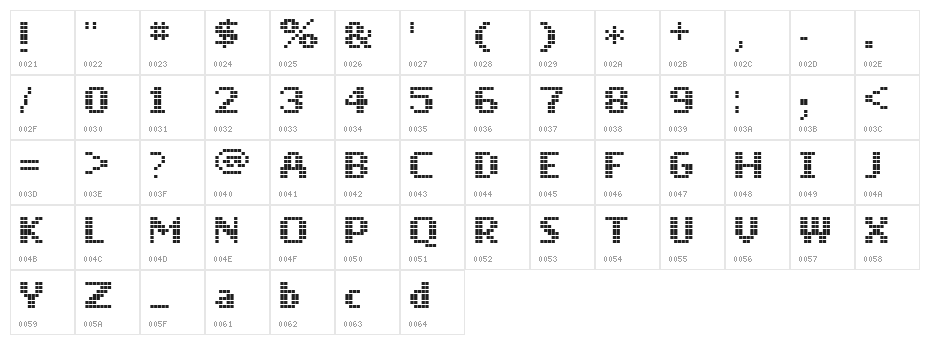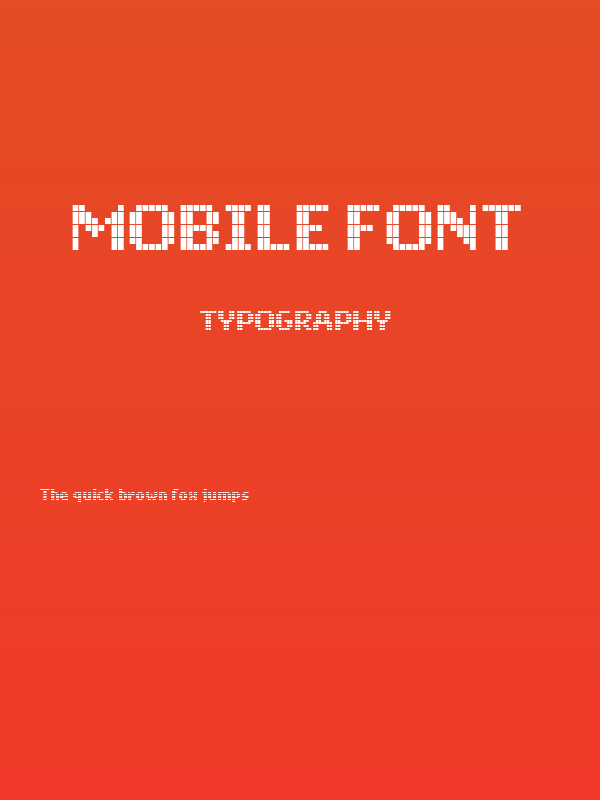
Mobile Font Font
| Stile generale | Retro, Digital |
| Caso d'uso | Headlines, Logos, Digital Art |
| Progetti proposti | Ideal for projects that aim to evoke a sense of nostalgia, such as retro-themed video games, digital art, or tech-related branding. It can also be used in modern designs that require a unique, eye-catching typeface. |